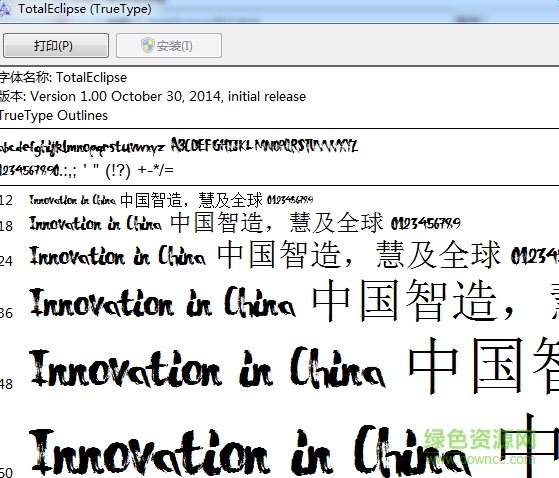
Totaleclipse字體是一款超好用的個(gè)性英文字體,該字體可以廣泛應(yīng)用于廣告設(shè)計(jì)、宣傳海報(bào)、ppt、影視制作以及任何使用文字的領(lǐng)域,有需要的朋友可以免費(fèi)下載收藏。
TotalEclipse字體是一款極具個(gè)性的字體,該字體十分飄逸,彰顯了自己的個(gè)性,有喜歡的朋友可以來綠色資源網(wǎng)下載使用!